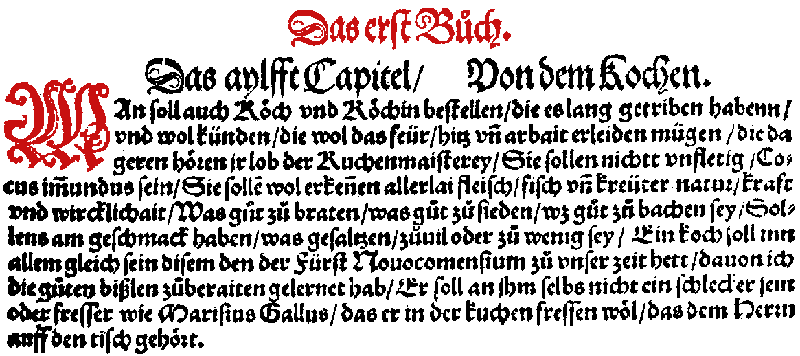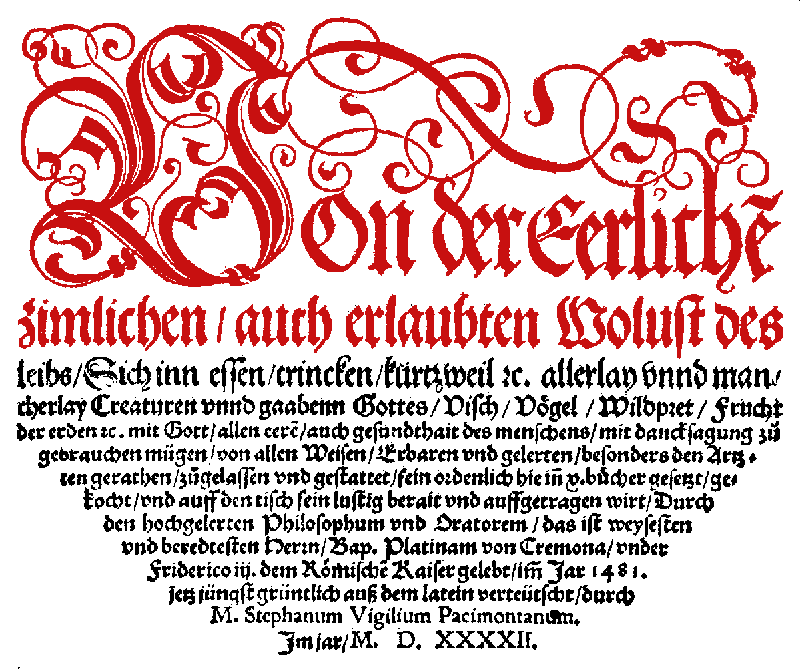
| Beim Lesen bitte beachten : Ein Kürzel-Strich über einem Buchstaben bedeutet eine Wortendung, meistens "n", manchmal "d". Derselbe Strich wird für Verdoppelungen verwendet, z.B. bei "erkennen". Als Doppellaute finden wir a mit einem kleinen e darüber = ä und ein u mit einem kleinen o darüber = uo. Außerdem gibt es ein u mit dem typischen u-Bogen, um den Buchstaben von n unterscheiden zu können. Die Worte "und" und "unter" wurden noch mit "v" geschrieben. Bei "ordenlich", "Natur" und "Herr" wird ein anderes r verwendet, als sonst. Das kleine f und das lange s sehen sich sehr ähnlich. Achtung, am Wortende steht ein rundes s (z.B. in "selbs"). Das kleine t ist leicht mit anderen Buchstaben zu verwechseln. |
| Von der Eehrlichen zimlichen / auch erlaubten Wolust des leibs / Sich inn essen / trincken / kurtzweil etc. allerlay vnnd man- cherlay Creaturen vnnd gaabenn Gottes / Visch / Vögel / Wildpret / Frucht der erden etc. mit Gott / allen eeren / auch gesundthait des menschens / mit dancksagung zu gebrauchen mügen / von allen Weisen / Erbaren ond gelerten / besonders den Ärtz- ten gerathen / zugelassen ond gestattet / fein ordenlich hie in v. bücher gesetzt / ge- kocht / vnd auff den tisch fein lustig berait vnd auffgetragen wirt / Durch den hochgelerten Philosophum vnd Oratorem / das ist weysesten vnd beredtesten Herrn / Bap. Platinam von Cremona / vnder Friderico III dem Römischen Kaiser gelebt / imm Jar 1481. jetz jüngst grüntlich auß dem latein verteütscht / durch M. Stephanum Vigilium Pacimontanum Im Jar / M.D.XXXXII. |
| das soll bedeuten : Dieses Buch handelt von der Wollust des Leibes, die ehrlich ist, die sich ziemt (= gutes Benehmen ist) und erlaubt ist. (Das Buch sagt) wie man beim essen, trinken und Zeitvertreib so manche Kreaturen (= Tiere) und Gaben Gottes, (als da sind) Fische, Vögel, Wildbret, Früchte der Erde usw., gottesfürchtig, ehrenhaft, die Gesundheit beachtend, mit Dank verwenden sollte (= gebrauchen möge). So wie es von allen ehrbaren und gelehrten weisen Leuten, besonders Ärzten, geraten und gestattet wird. Es wurde in Bücher geschrieben, wie gekocht, zubereitet und aufgetragen wird. (Verfaßt) durch den hochgelehrten Philosophen und Oratorem -das sind die weisesten und beredesten Herren- Bap. (= Baptist ?) Platina von Cremona, der im Jahre 1481 unter dem römischen Kaiser Friedrich III gedient hat. Jetzt neu gründlich vom lateinischen ins deutsche übersetzt durch Meister Stephan Vigilium Pacimontanum. Im Jahre 1542. |
| Das erst Buoch. / Das aylffte Capitel / Von dem Kochen MAn soll auch Köch und Köchin bestellen / die es lang getriben habenn / vnd wol künden / die wol das feür / hitz ond arbait erleiden mügen / die da geren hören jr lob der Kuchenmaisterrey / Sie sollen nichtt vnfletig / Co- cus immundus sein / Sie sollen wol erkennen allerlai fleisch / fisch ond kreüter natur / kraft vnd wircklichait / Was guot zu braten / was guod zu sieden / wz guot zu bachen sey / Sol- lens am geschmack haben / was gesaltzen / zuvil oder zu wenig sey / Ein koch soll inn allem gleich sein disem den der Fürst Novocomensium zu vnser zeit hett / davon ich die guoten bißlen zuberaiten gelernet hab / Er soll an jhm selbs nicht ein schlecker sein oder fresser wie Marisius Gallus / das er in der kuchen fressen wöl / das dem Herrn auff den tisch gehört. |
| das soll bedeuten : Das erste Buch / Das elfte Kapitel / Vom Kochen Man sollte einen Koch oder eine Köchin einstellen, die es (diesen Beruf) schon lange betrieben haben. Die sagen, daß sie das Feuer, die Hitze und die Arbeit (in der Hitze) ertragen können. Die gerne ihr Lob über die Kochkunst hören lassen. Sie sollen nicht unflätig (schmutziger Koch) sein. Sie sollen gut erkennen die Arten von Fleisch und Fisch, die Natur der Kräuter, ihre Würzkraft und Geschmack. (Sie sollten wissen) was gut braten, was gut zu kochen und gut zu backen ist. Sie sollten schmecken können, ob es (das Essen) zuviel oder zuwenig gesalzen ist. Ein Koch sollte so sein, wie der Koch, den der Fürst Novocomensium zur Zeit hat, von dem ich die guten Bissen zuzubereiten gelernt habe. Er (der Koch) sollte kein Schleckermaul oder ein Fresser sein, wie Marisius Gallus, der schon in der Küche essen möchte, was auf den Tisch seines Herrn gehört. |